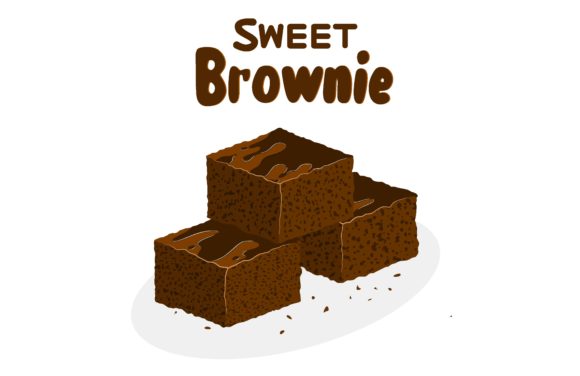
Chocolate Brownies
適切なデザイン要素を見つけるのは難しい場合がありますが、Chocolate Browniesは作品を即座に引き立てる優れたコレクションを提供します。
POD(オンデマンド印刷)製品、結婚式の招待状、またはソーシャルメディアのグラフィックを作成している場合でも、Chocolate Browniesは理想的です。